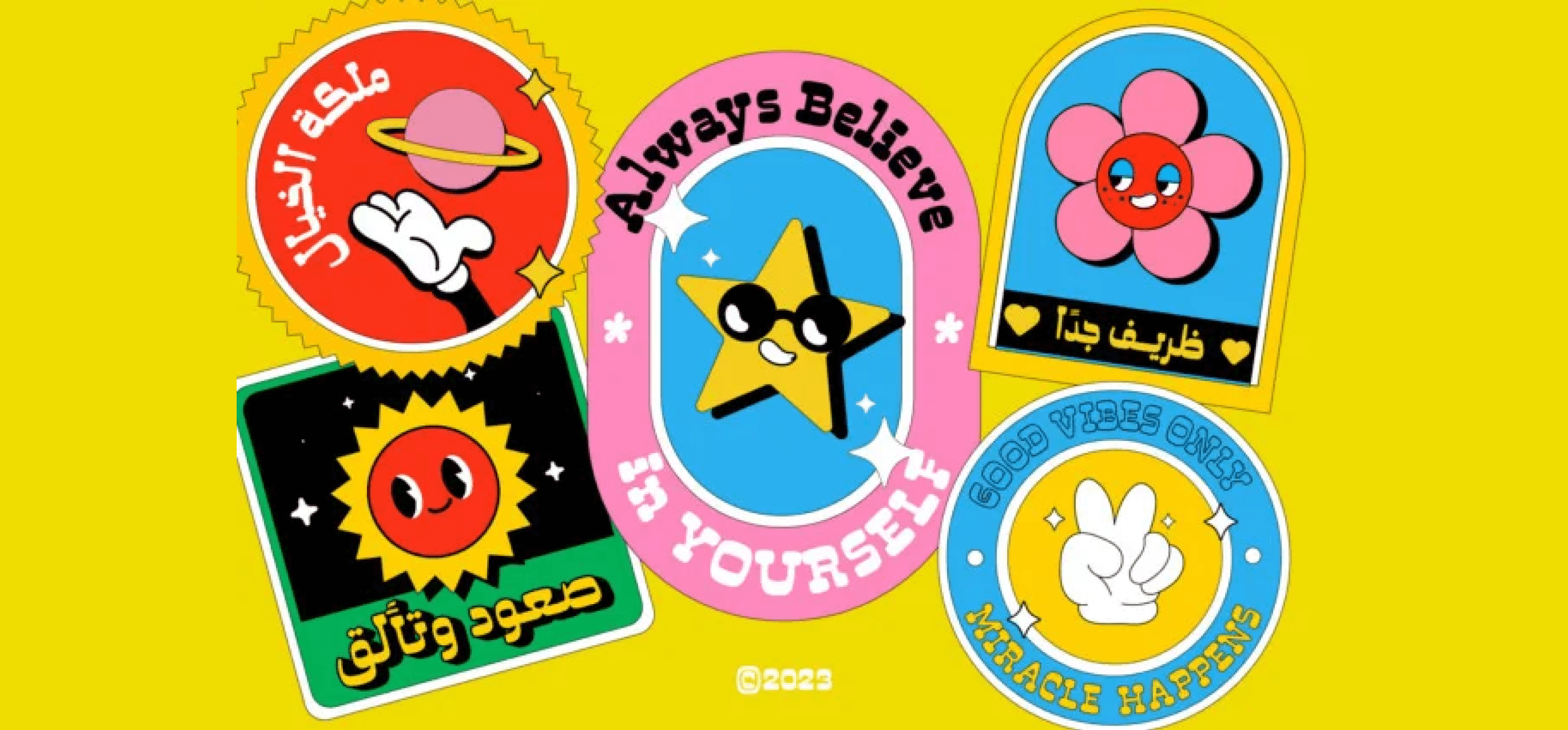
خط Muraba هو خط عربي يجمع بين الأسلوب العصري الجريء وسحر الطابع الكلاسيكي ليمنح التصميم مظهرًا أنيقًا وخالدًا. يتميز بحروف ذات سيريف مربعة وسميكة مصممة بعناية تلفت الأنظار وتضفي لمسة زخرفية راقية.
تم تطوير الخط بإضافة محارف عربية إضافية لدعم لغات متعددة مثل العربية، الأوردو، الكردية، الفارسية، والجاوي، مما يجعله خيارًا مثاليًا للتصميمات العالمية والإبداعية.
سواء استُخدم في العناوين، أو الشعارات، أو النصوص البارزة، فإن Muraba يمنح كل مشروع طابعًا فريدًا وحضورًا بصريًا قويًا.